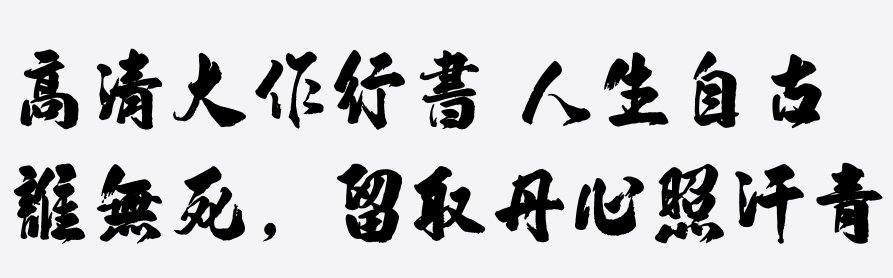
做标题的字体一定要显得大气才能引人注目。在这里,我们分享一款大字体和时尚标题的大字体,希望您能从中得到启发。
汉标高清大作行书,一款带有书法味道的纯手写高清大字体,笔画中保留了过多的笔锋,字体厚重、饱满。因为是纯手写的原因,它独特的气质更与其他字体不同,看似统一,其实各有各的味道,每个字都可以独具风情。字由字在,大到自然,便是对它最好的诠释。